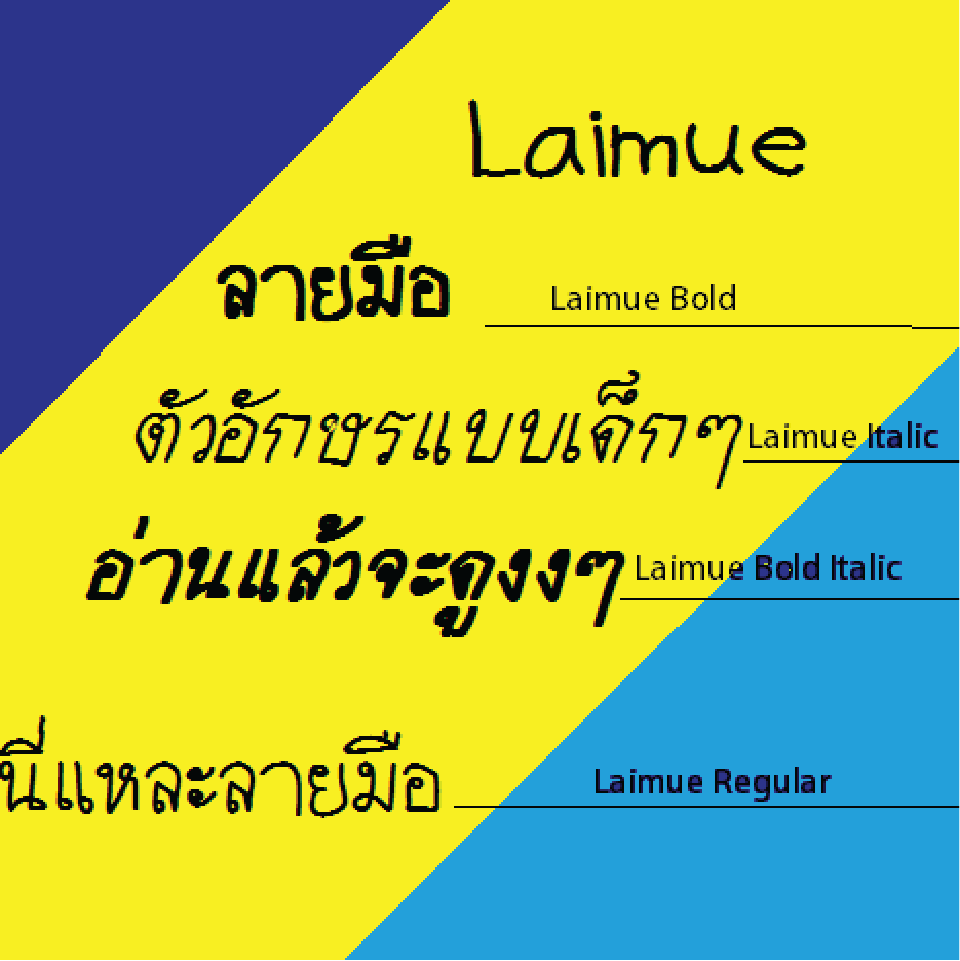
ฟอนต์ ลายมือ
ชื่อฟอนต์ : Laimue
แรงบันดาลใจ : คือผมเห็นน้องเพิ่งหัดเขียนตัวอักษร เห็นมันน่ารักดี เลยสแกนลงคอมแล้วจัดลง template เป็นฟอนต์ครับ
อ้อ ; ฟอนต์รุ่นแรกขนาดช่องไฟอาจยังไม่ค่อยชัดเจนก็เลย เบี้ยวๆ บ้าง นะครับ ;D